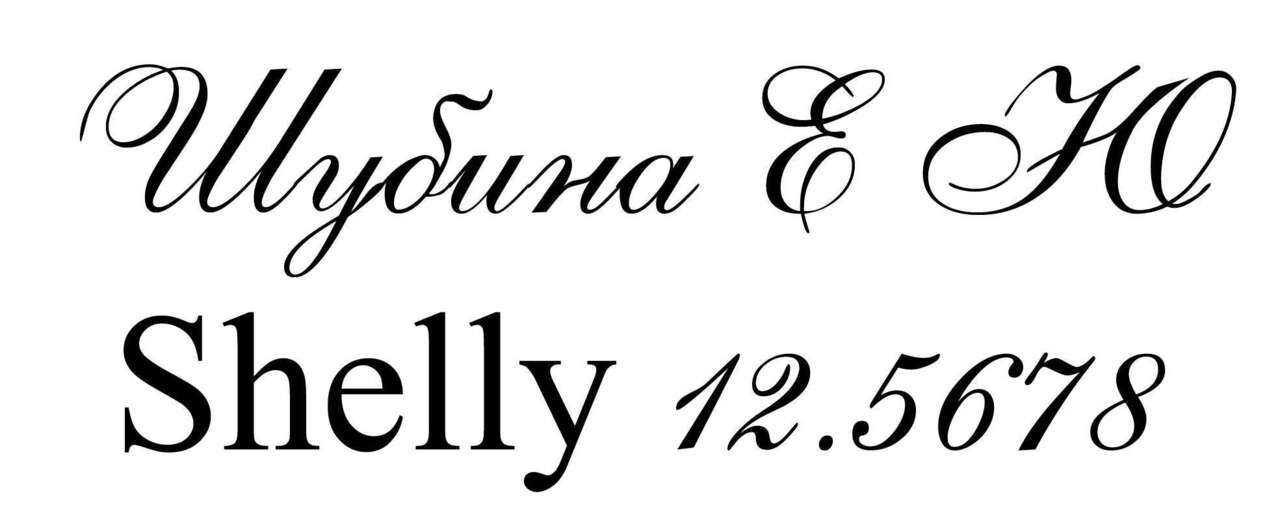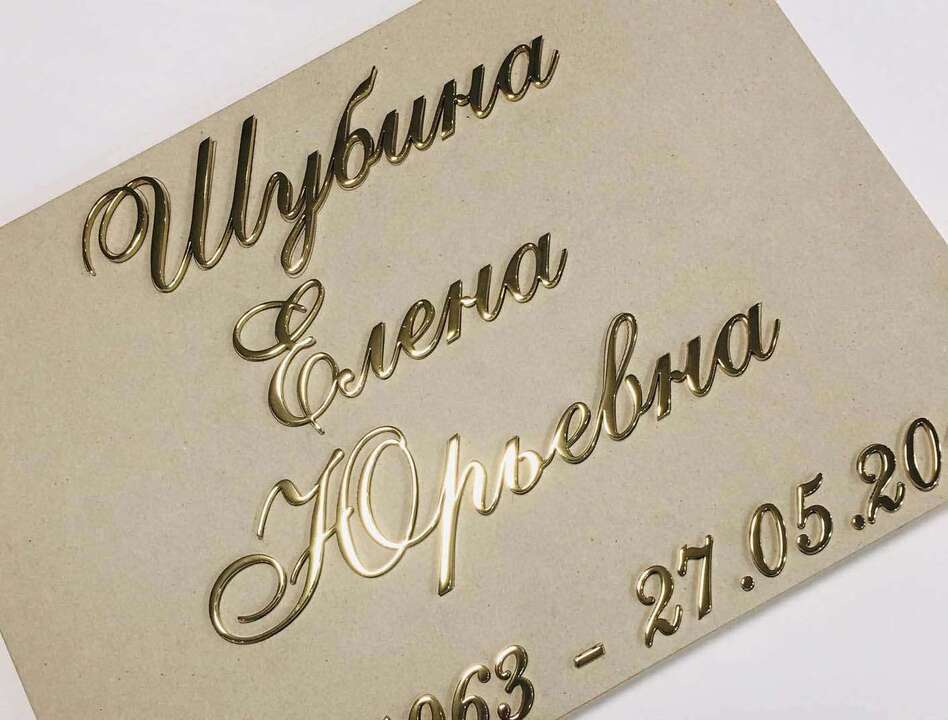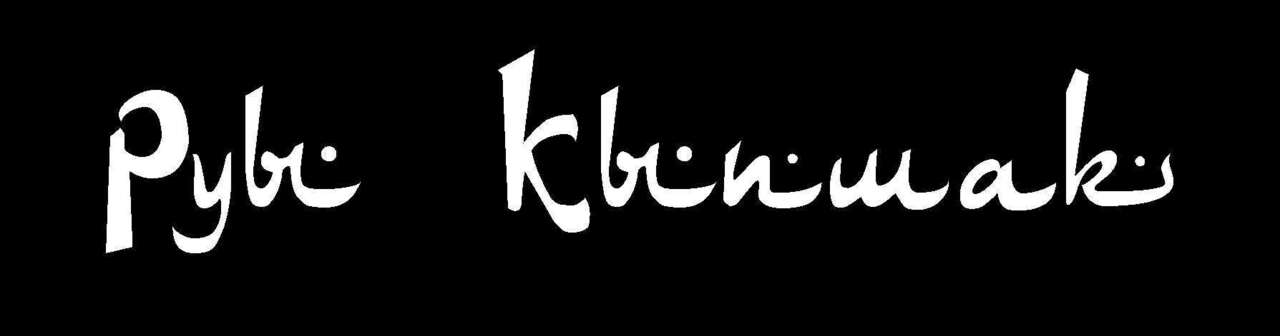
mikki Опубликовано 24 декабря, 2024 (изменено) Подскажите пожалуйста , что за шрифт ? Изменено 24 декабря, 2024 пользователем mikki
leekbez Опубликовано 24 декабря, 2024 (изменено) @mikki Shelly Изменено 24 декабря, 2024 пользователем leekbez
Смешарик Опубликовано 24 декабря, 2024 10 часов назад, алена сказал: @Смешарик А можно посмотреть, что за шрифт? обычный, ничего особенного, столетний)))) но как то не сложилось у меня сегодня с ним)))))))))))
Melnichsd Опубликовано 28 декабря, 2024 Добрый день, не подскажите подобный шрифт?
АлександрTv Опубликовано 5 января, 2025 Не могу нигде найти такой шрифт. Заранее благодарю!!!
fenix Опубликовано 6 января, 2025 Всех с Новым годом, счастья, здоровья, любви, творческих успехов! Пожалуйста помогите найти шрифт и его название.
Александра Фот Опубликовано 6 января, 2025 6 часов назад, fenix сказал: Всех с Новым годом, счастья, здоровья, любви, творческих успехов! Пожалуйста помогите найти шрифт и его название. Это ручная работа. Могу подготовить для гравировки 1
Iren1611 Опубликовано 21 января, 2025 Доброго времени суток! Помогите найти шрифт... Два дня рою весь простор интернета и без результата... ((( DS Arabic не предлагать - начертание некоторых букв не совпадает!! Заранее благодарю за любую помощь!!
Iren1611 Опубликовано 21 января, 2025 @Storn Диагноз не утешительный! (( Значит, придется ручками поработать... Благодарю!!
алена Опубликовано 21 января, 2025 @Iren1611 Посмотрите вот этот Pehlevi Cyrillic 1
Iren1611 Опубликовано 21 января, 2025 @алена Видела... немного не то, но шрифт сам по себе красивый, сохранила на всякий пожарный... Благодарю! 1
алена Опубликовано 21 января, 2025 @Iren1611 По моему, судя по образцу, присутствуют элементы английских букв. Может просто набирали в перемешку латиница-кириллица?